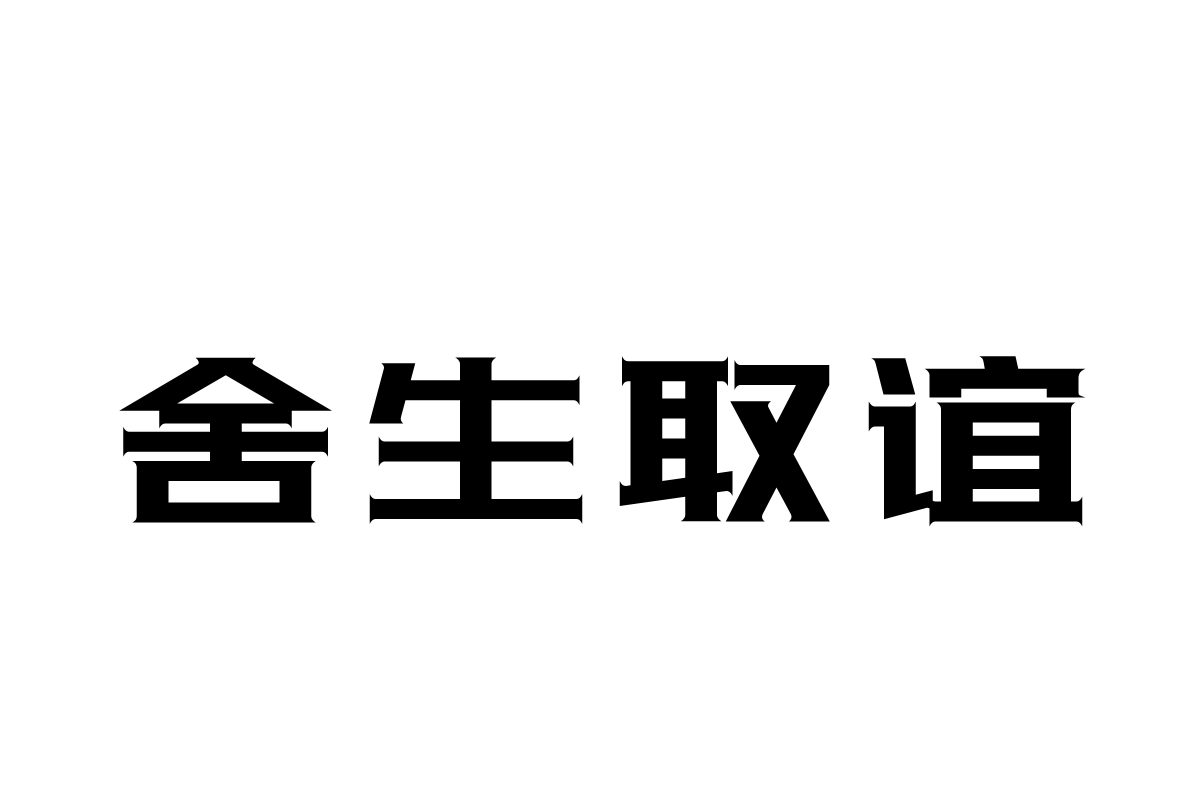
三极光耀简体版是一款专为中文书写设计的字体,它采用了现代的设计元素和创新的排版方式,使得文字更加清晰、易读。该字体具有多种字重和行距选择,可以满足不同场景下的需求。此外,三极光耀简体版还注重细节处理,如笔画粗细、间距调整等,以确保文字的美观性和可读性。总的来说,三极光耀简体版是一款值得推荐的中文字体。